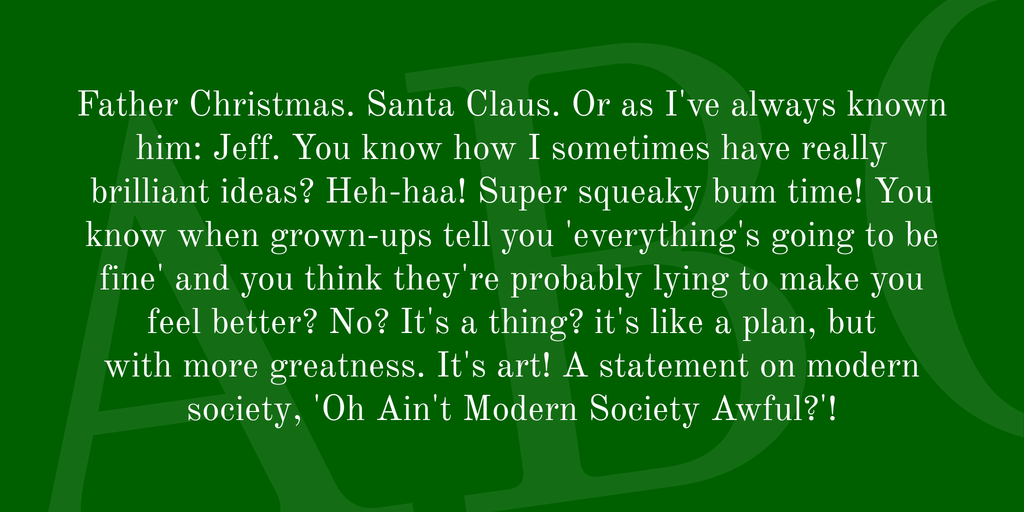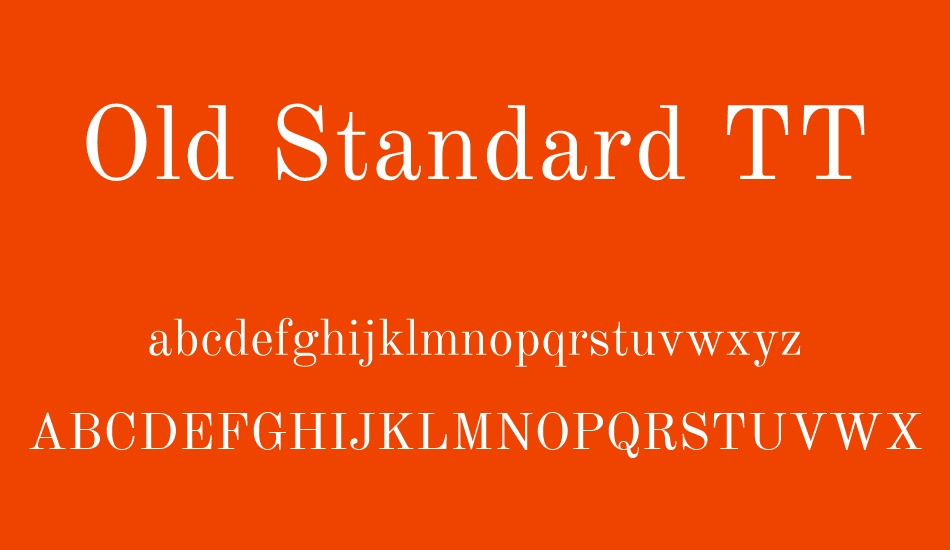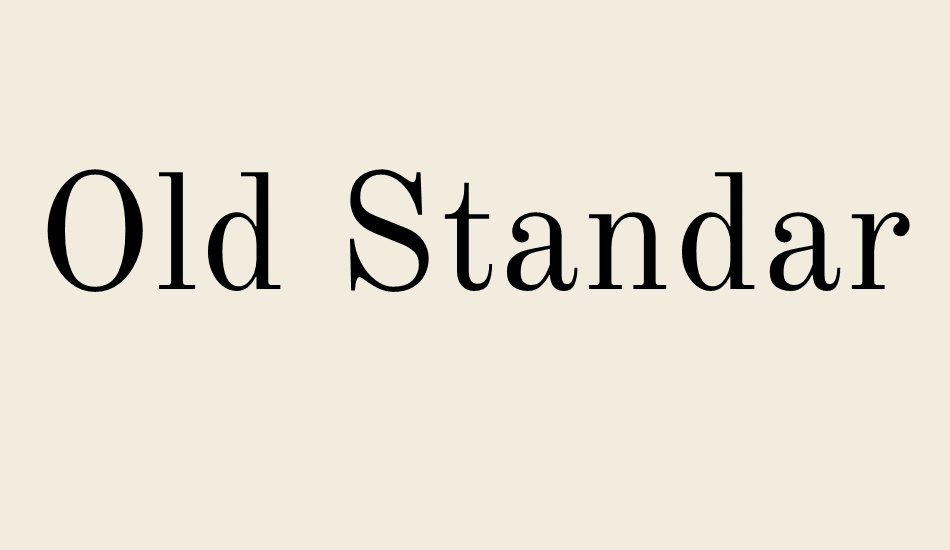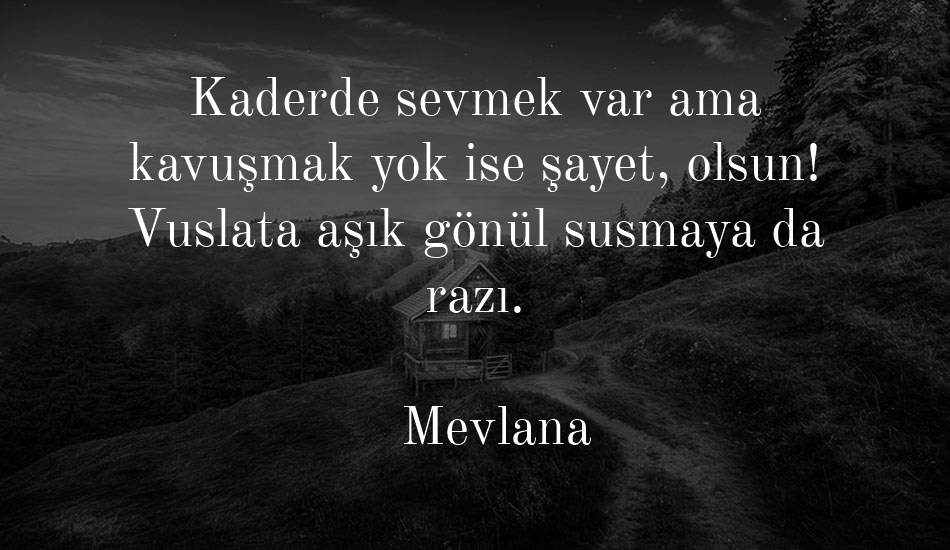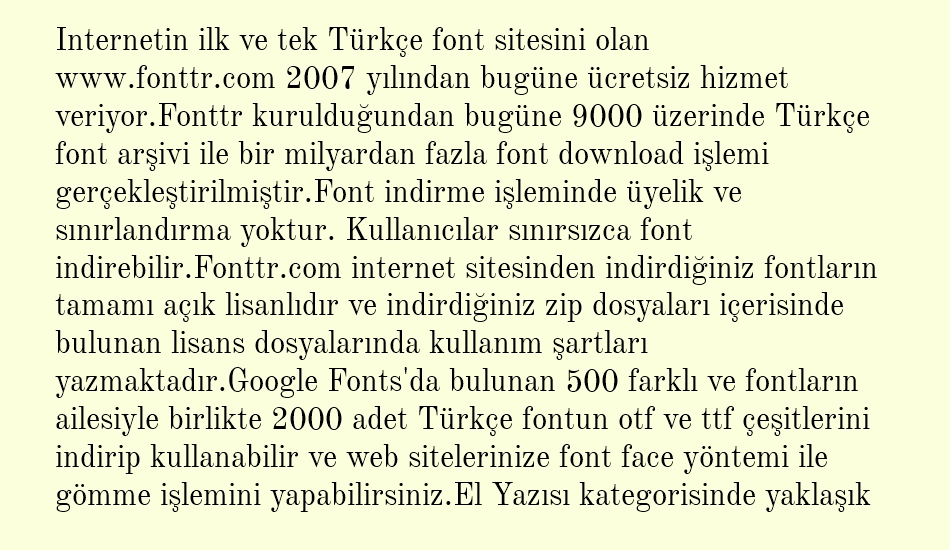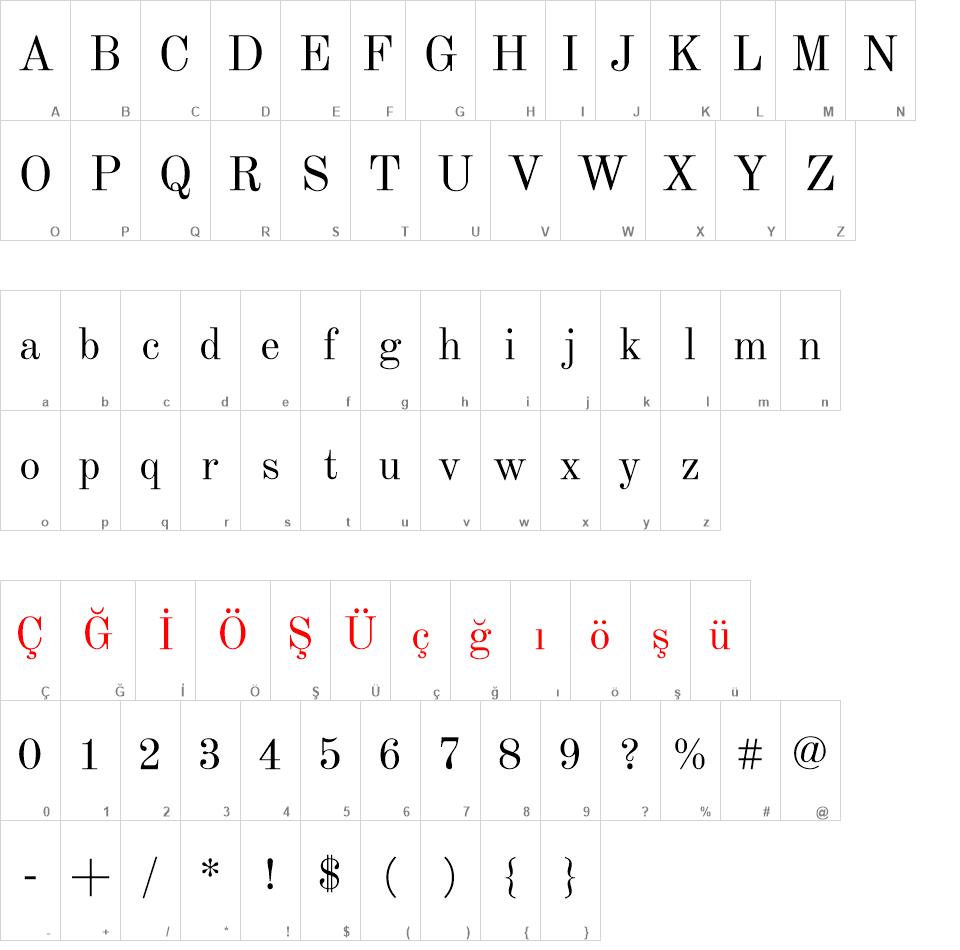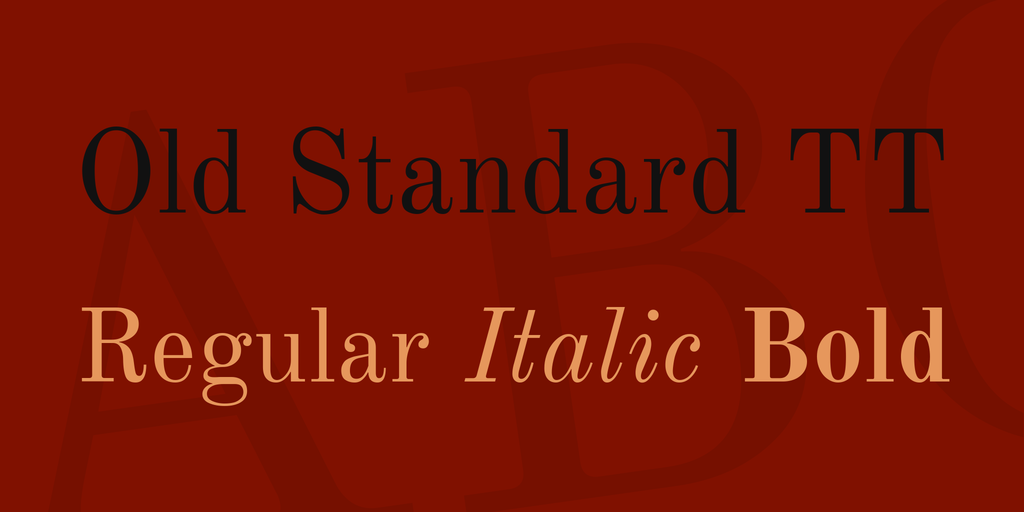
Eski Standart, 19. yüzyılın sonu ve 20. yüzyılın başlarında çeşitli yayımlarda yaygın olarak kullanılan, serif yazı biçimlerinin modern (klasik) stilinin belirli bir türünü üretir; ancak daha sonra neredeyse tamamen terk edilmiştir. Bununla birlikte, bu harf türünün hala en az iki avantajı vardır:
Bilimsel belgeleri, özellikle sosyal ve insancıl bilimlerde dizgilemek için iyi bir seçim olarak kabul edilebilir; zira belirli özellikleri insanların gözünde öğrendikleri eski kitaplarla yakından ilişkilidir;
Yunan ve Kiril harflerinin en güzel örnekleri hepsi klasik tarza dayanıyordu, bu betiklerde "Modern" yazı tipleri çağdaş (örneğin Times tabanlı) tasarımlardan çok daha uygundur.
"Old Standard" ismi, aynı Modern stilin biraz farklı bir türünü temsil eden Sovyet tipografisinde yaygın olarak kullanılan "Obyknovennaya Novaya" ("Yeni Standart") yazı karakterinin yerine seçildi. Elbette bu isim çok orijinal görünmüyor, ancak 20. yüzyılın başlarındaki en yaygın harf türünün canlandırılması için iyi bir seçim gibi görünüyor.